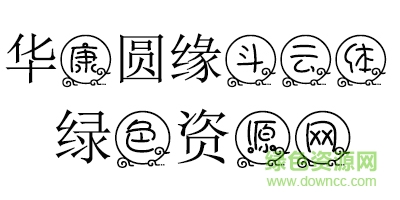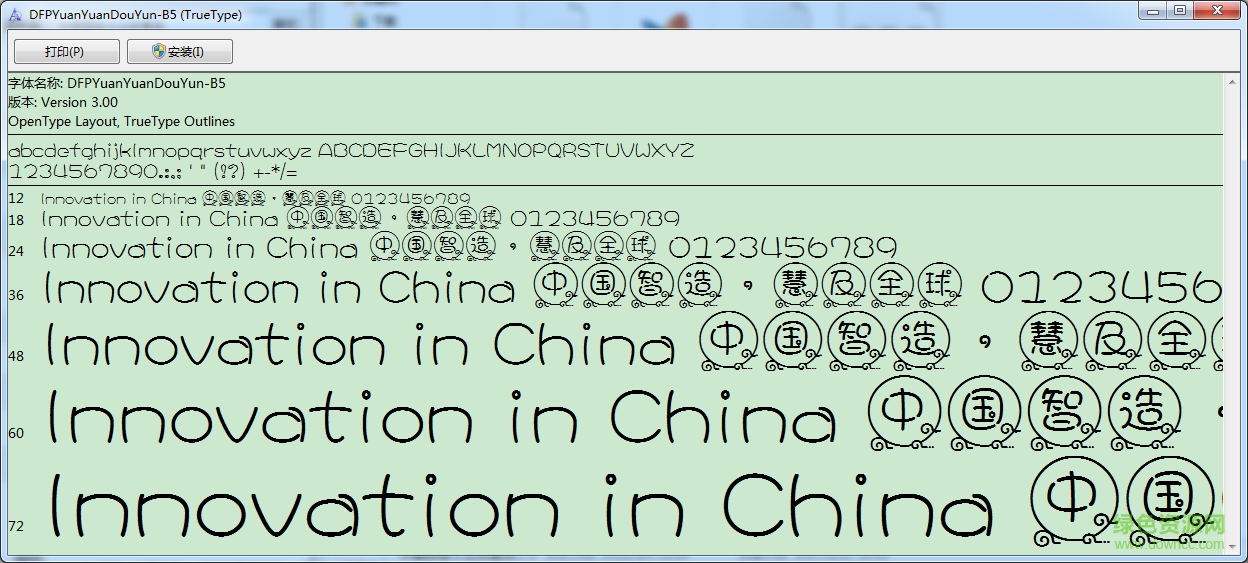
華康圓緣斗云體繁體是一款獨具特色的藝術(shù)字體,這款字體極具創(chuàng)意和藝術(shù)感,字體外邊帶來一個圓圈,并且?guī)в邢樵茍D案,看起來非常有個性,整體效果非常出色,喜歡這款字體的朋友歡迎來綠色資源網(wǎng)下載體驗吧!
華康圓緣斗云體繁體是一款Windows系統(tǒng)環(huán)境下的字體工具。是一款用于流云設(shè)計方面的字體,字體外觀十分漂亮,從字體名稱來看,字體有一個圓圓的祥云包圍著,充滿了祥和的感覺。